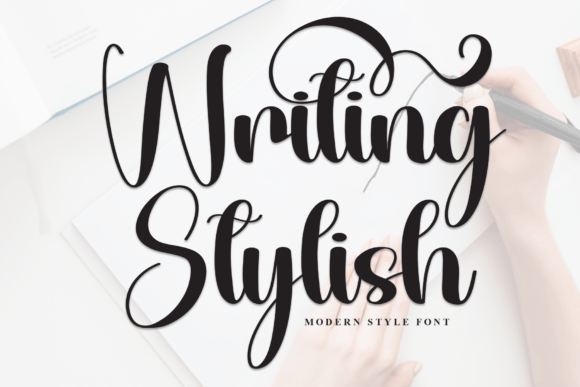
Writing Stylish
Die richtigen Designelemente zu finden, kann eine Herausforderung sein, aber Writing Stylish bietet eine außergewöhnliche Sammlung, die Ihre Arbeit sofort aufwertet.
Egal, ob Sie POD-Produkte (Print on Demand), Hochzeitseinladungen oder Social-Media-Grafiken erstellen, Writing Stylish ist die ideale Wahl.